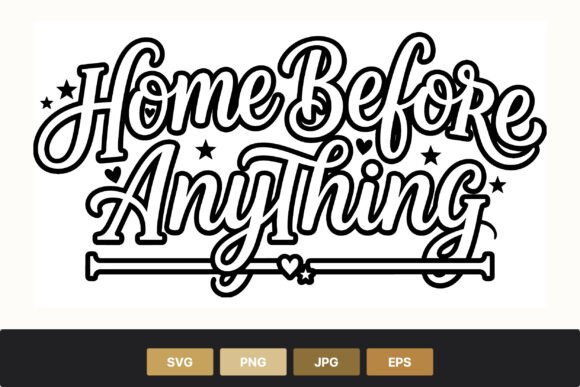
Home Before Anything Script Letters
Mencari elemen reka bentuk yang sesuai boleh menjadi mencabar, tetapi Home Before Anything Script Letters menawarkan koleksi luar biasa yang menaik taraf karya anda serta-merta.
Sama ada anda mencipta produk POD (Print on Demand), jemputan perkahwinan atau grafik media sosial, Home Before Anything Script Letters amat bersesuaian.